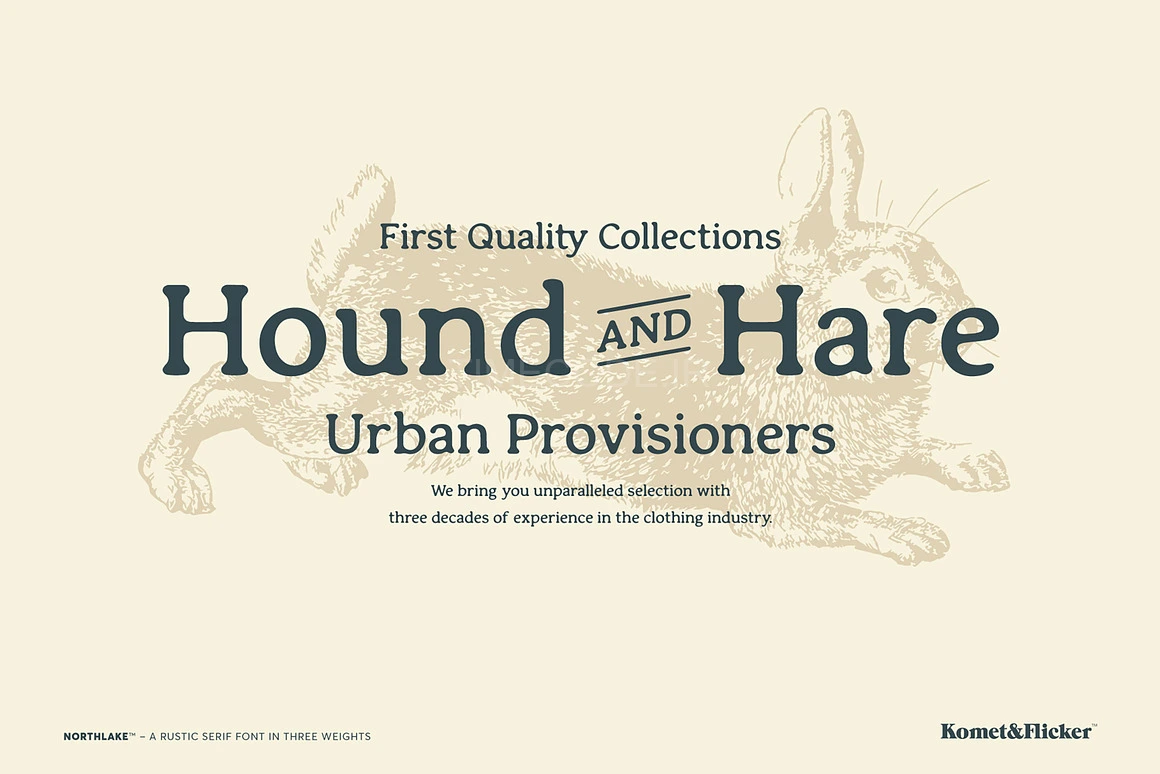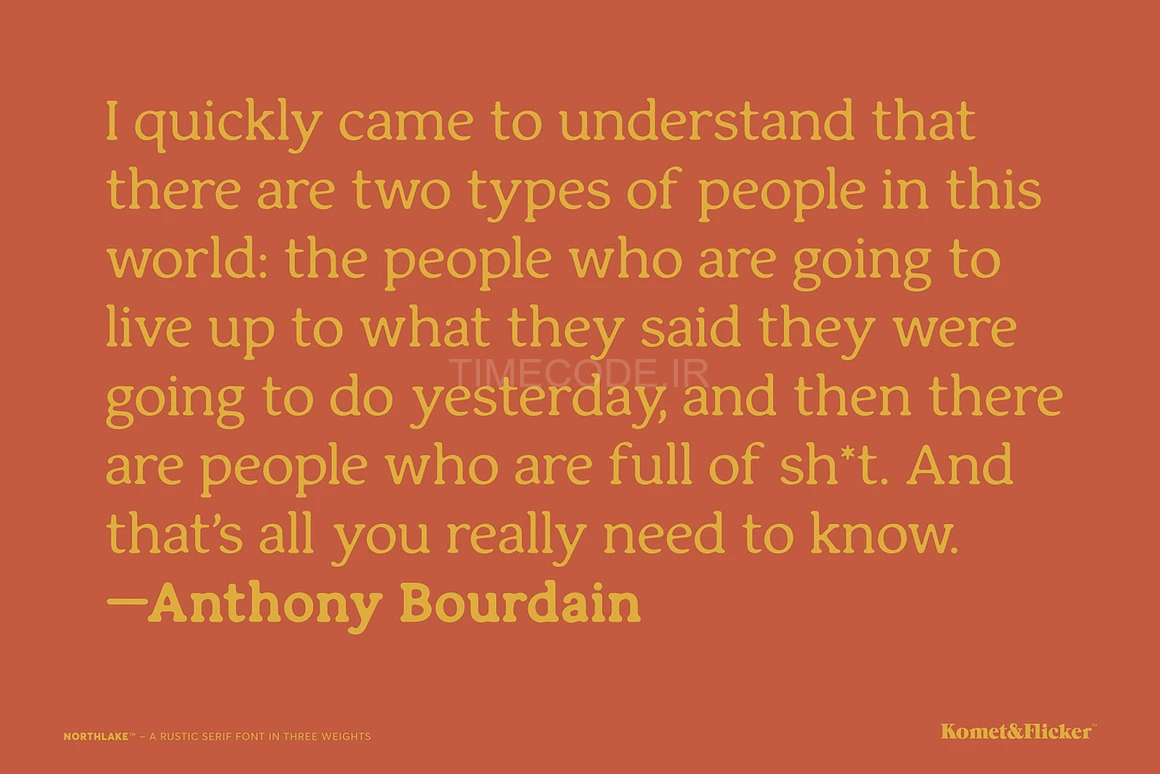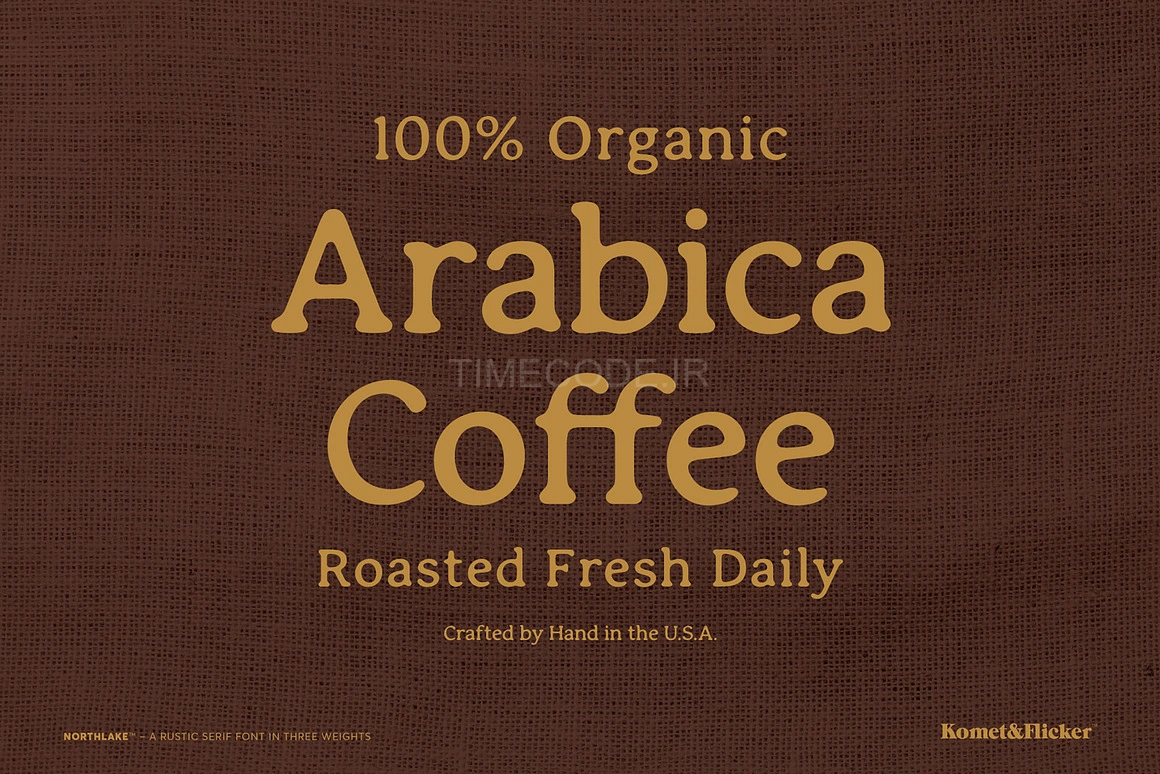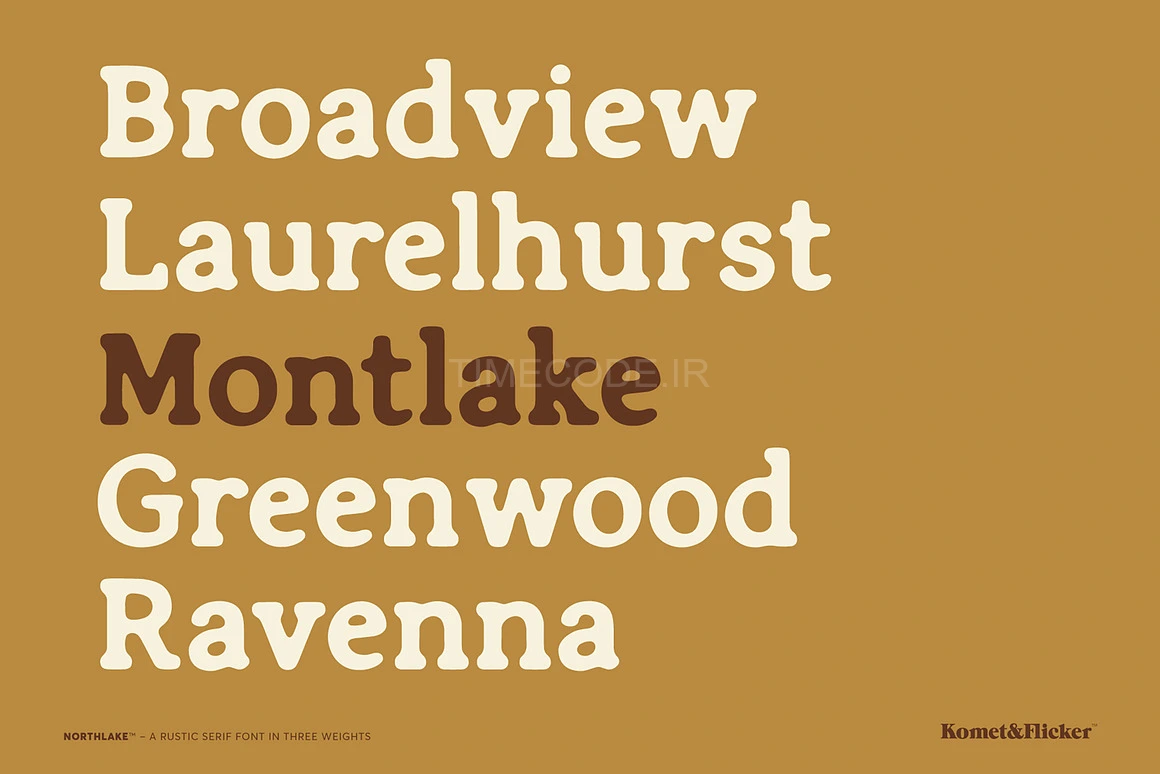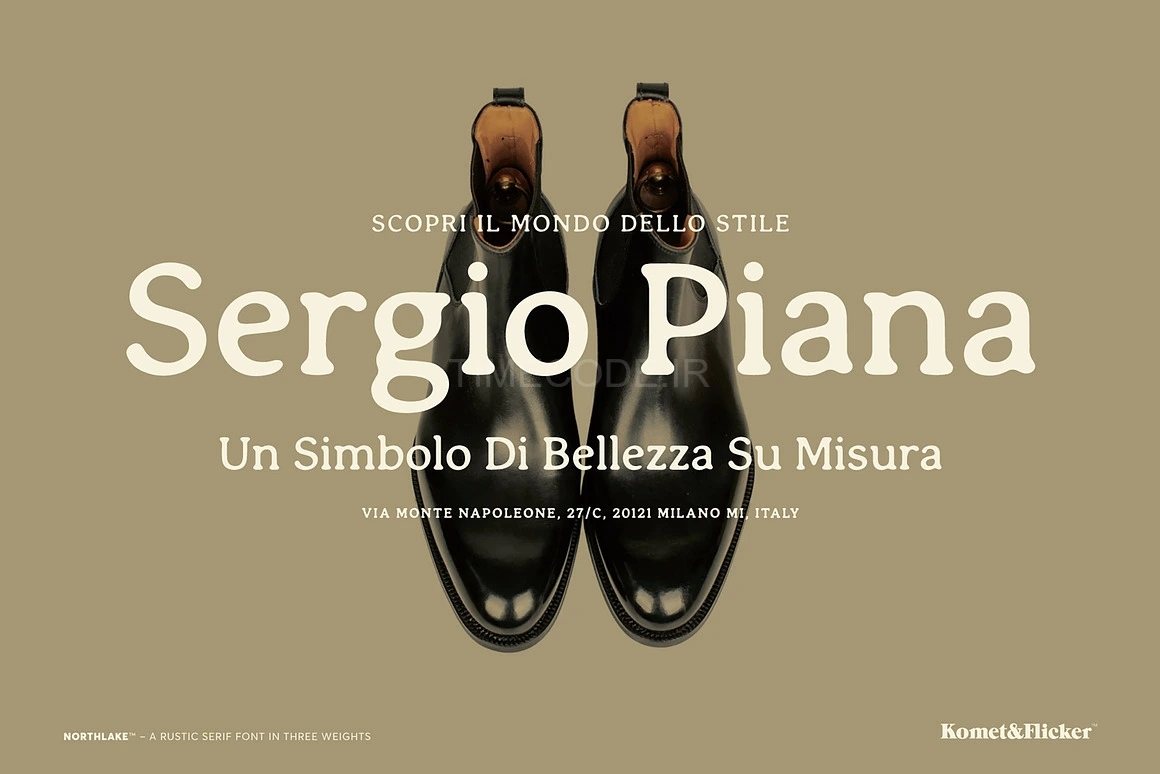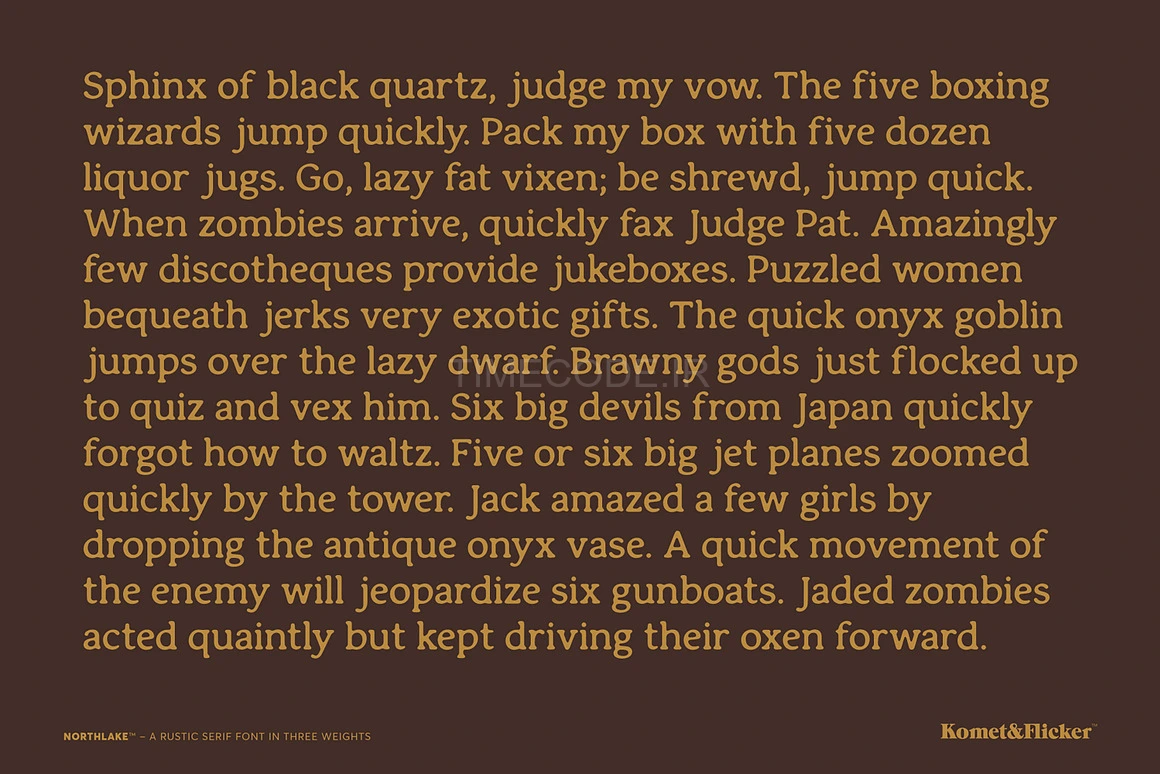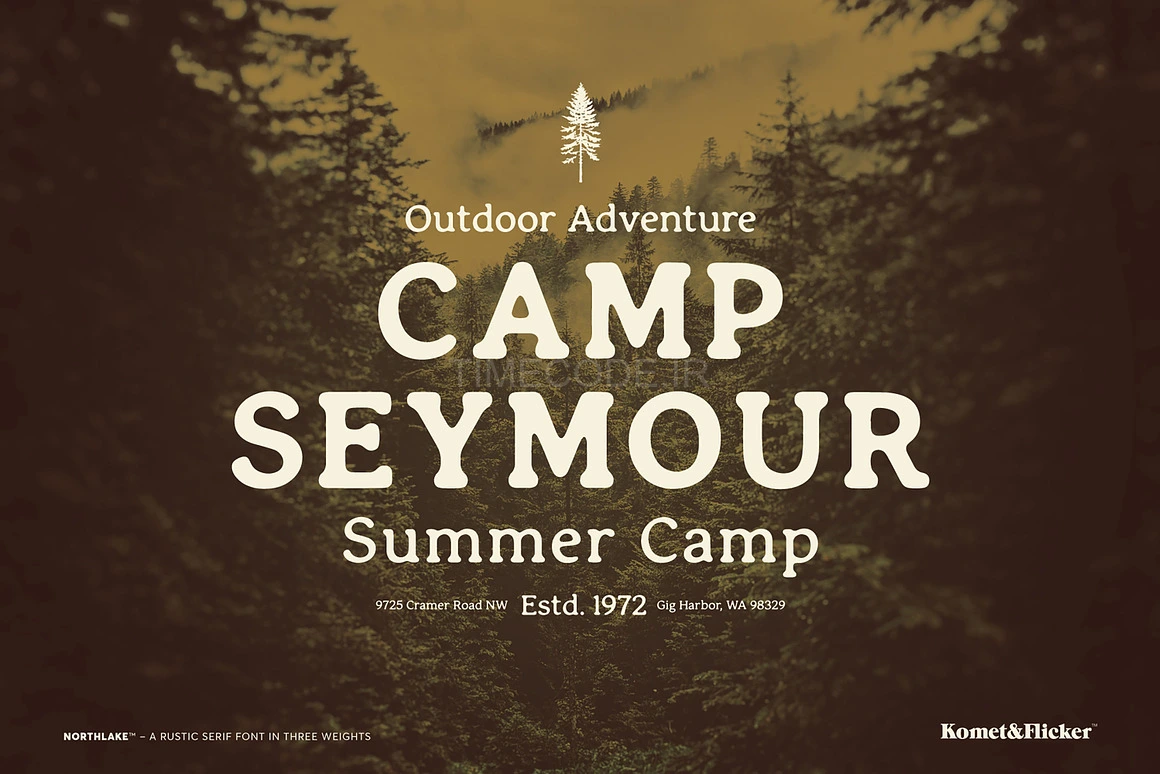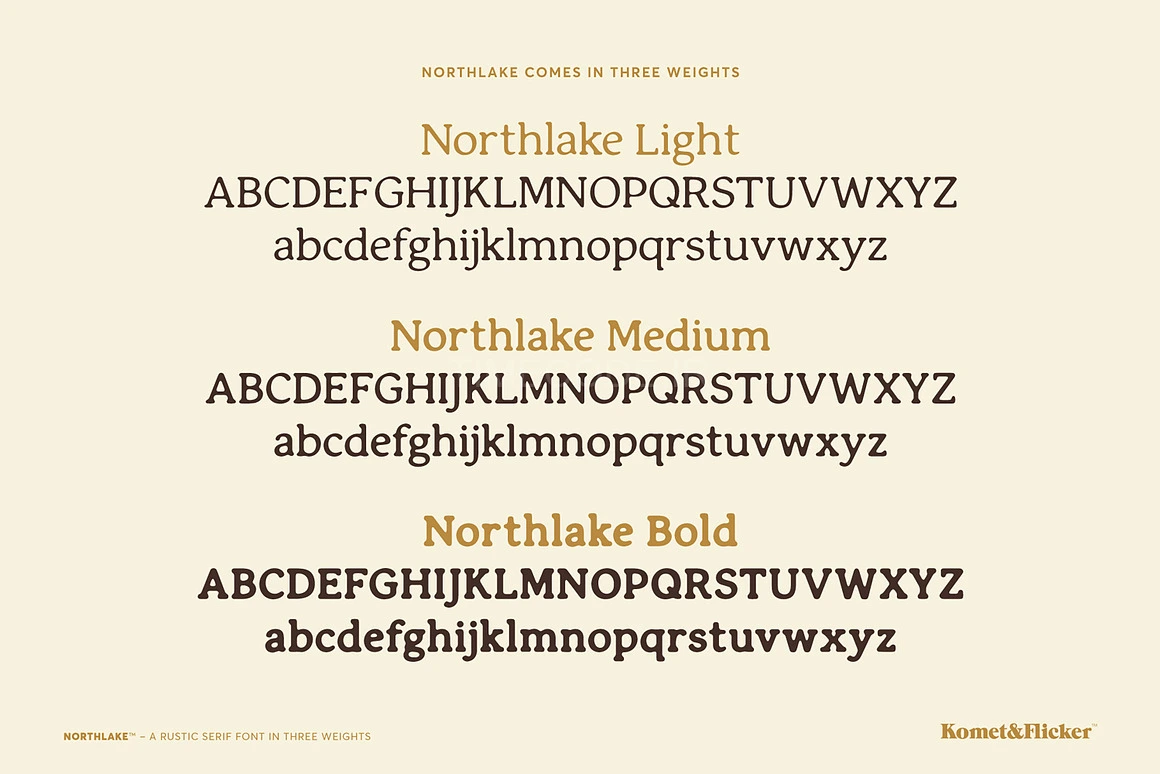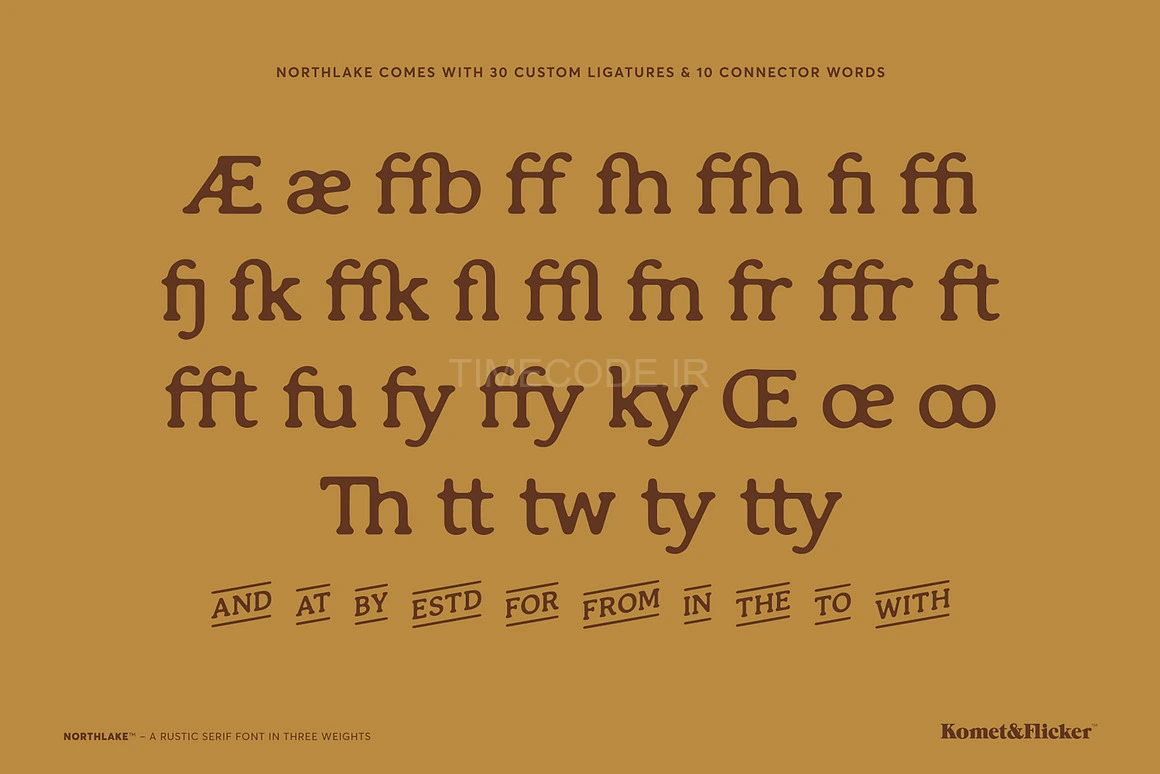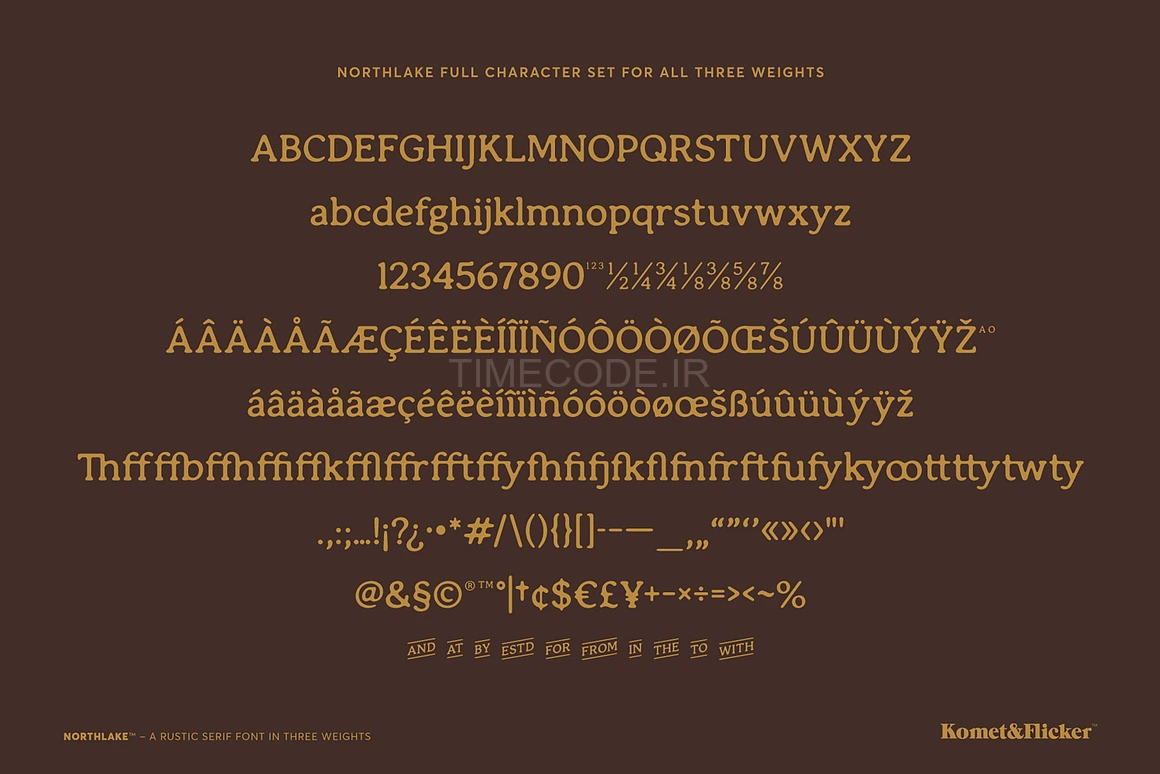
• Northlake - A Rustic Serif Font
فونت انگلیسی وینتج جوهری
Northlake با لبه‌های نرم و گرد و حال و هوای وینتج خود، گرما و اصالت یک اثر کلاسیک دوست‌داشتنی را القا می‌کند. چه در حال طراحی تیترهای برجسته باشید و چه مشغول ساخت بلوک‌های متنی طولانی‌تر، Northlake تطبیق‌پذیری و شخصیت را برای هر پروژه‌ای به ارمغان می‌آورد.
Northlake که در سه وزن با دقت طراحی شده‌ی Light، Medium و Bold موجود است، به شما این امکان را می‌دهد که طراحی خود را به راحتی تنظیم کنید. لبه‌های گرد آن به هر کاراکتر حسی نرم و دوستانه می‌بخشد، در حالی که سریف‌های استوار آن، حسی از سنت و قدرت را به تایپوگرافی شما می‌آورند.
Northlake با مجموعه‌ی گسترده‌ی خود شامل 30 لیگچر (حروف ترکیبی) سفارشی، که برای بهبود جریان و زیبایی‌شناسی تایپوگرافی شما طراحی شده‌اند، برجسته می‌شود. این لیگچرهای با دقت ساخته شده، ظرافت را به متن شما اضافه کرده و ظاهری روان‌تر و منسجم‌تر را تضمین می‌کنند. علاوه بر این، این فونت شامل مجموعه‌ای از 10 کلمه‌ی ربط رایج مانند “and”، “the” و “with” است که به ایجاد انتقال‌های یکپارچه بین کلمات برای رسیدن به حسی طبیعی‌تر و ارگانیک‌تر کمک می‌کنند. این موارد اضافه شده‌ی هوشمندانه، Northlake را نه تنها از نظر بصری چشم‌نواز، بلکه بسیار کاربردی نیز می‌سازند و تضمین می‌کنند که طراحی شما به روانی جریان یابد و انسجام خود را حفظ کند.
چه در حال کار بر روی برندینگ، طراحی تحریریه، یا خلق یک اثر با الهام از سبک وینتج باشید، Northlake تعادل کاملی از ظرافت، خوانایی و شخصیت را به ارمغان می‌آورد.
این فونت در سه وزن ارائه می‌شود
• Northlake Light
• Northlake Regular
• Northlake Bold
این فونت شامل موارد زیر است
• تمام حروف بزرگ لاتین پایه از A تا Z
• کاراکترهای منتخب مخصوص اروپایی
• اعداد، علائم نگارشی و نمادهای منتخب
• مجموعه‌ای از 30 لیگچر سفارشی
Introducing Northlake, a rustic serif font with a timeless charm. With its smooth, round edges and vintage appeal, Northlake evokes the warmth and authenticity of a well-worn classic. Whether you're designing bold headlines or crafting longer blocks of text, Northlake offers versatility and personality for any project.
Available in three thoughtfully crafted weights: Light, Medium, and Bold, Northlake allows you to fine-tune your design with ease. Its rounded edges give each character a soft, approachable feel, while its sturdy serifs bring a sense of tradition and strength to your type.
Northlake stands out with its extensive set of 30 custom ligatures, designed to enhance the flow and aesthetic of your typography. These carefully crafted ligatures add sophistication and ensure a smoother, more cohesive appearance in your text. Additionally, this font includes a set of 10 common connecting words, such as "and", "the", and "with", which help to create seamless transitions between words for a more natural, organic feel. These thoughtful additions make Northlake not only visually striking but also highly functional, ensuring your design flows effortlessly and maintains consistency.
Whether you're working on branding, editorial design, or crafting a vintage-inspired piece, Northlake brings the perfect balance of elegance, readability, and character.
THIS FONT COMES IN THREE WEIGHTS
- Northlake Light
- Northlake Regular
- Northlake Bold
THIS FONT INCLUDES
- Full A-Z uppercase basic latin characters
- Select European specific characters
- Numbers, punctuation, and select symbols
- A set of 30 custom ligatures